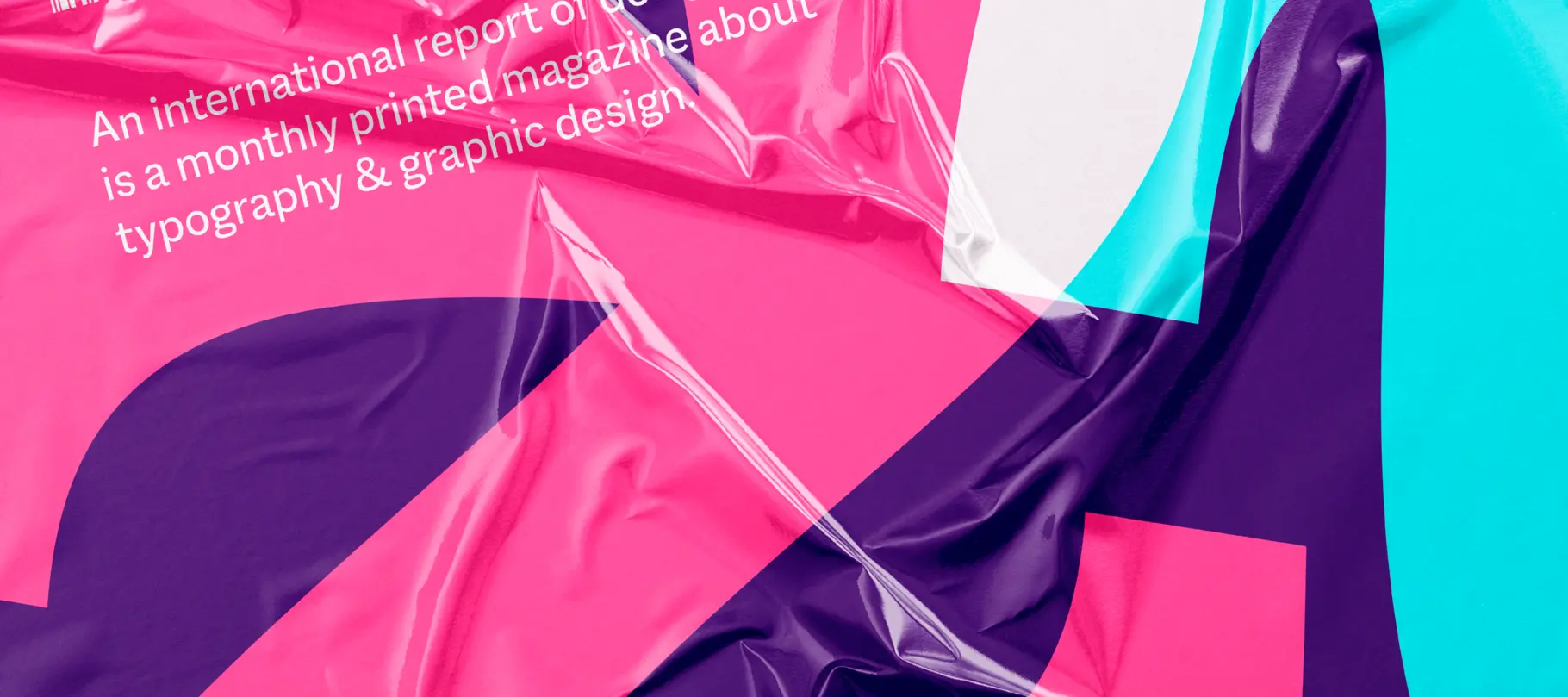
Macklin™
Inspiriert von der Tradition. Entwickelt für modernes Design.
Macklin ist inspiriert von der Zeit, als die Schrift von den Seiten der Bücher auf Großplakate und Anzeigen drängte. Mit einer klaren Weiterentwicklung gegenüber ihren typografischen Vorbildern ist die Superfamilie Macklin mit ihren scharfen und doch eleganten Formen bestens geeignet für zeitgenössisches und modernes Design.
Die Superfamilie Macklin umfasst 4 Unterfamilien mit 9 Strichstärken von sehr fein bis sehr fett: Insgesamt 54 Schriften, die eine breite Palette an Möglichkeiten für den Gestalter eröffnen.
Die Arbeit am Konzept der Macklin begann mit der Erforschung historischer Unterlagen aus Europa und speziell Großbritannien zu Beginn des 19. Jahrhunderts, insbesondere der Arbeit des Schriftgestalters und Gießereibesitzers Vincent Figgins.
Es war eine Zeit großer sozialer Veränderungen – der Beginn der industriellen Revolution. Eine Zeit, in der Hersteller und Werbetreibende plötzlich begannen traditionelle Handschrift- oder Kalligraphie Schriften zu ersetzen und eine andere, mutige und aufmerksamkeitsstarke Typografie forderten. Typografen experimentierten mit innovativen neuen Schriftstilen, wie Fat Faces und Italiennes. Sie entwickelten viele Stile, die von Marken und Designern auch heute noch verwendet werden, wie z. B. stark serifenbetonte oder serifenlose Schriften.
Verlomme zollt Figgins‘ Arbeit mit der Macklin Respekt, überträgt das Designkonzept jedoch in die Neuzeit. Jede Unterfamilie wurde aus dem gleichen Skelett entworfen. Das gibt den Designern eine breite Palette an Möglichkeiten. Sie können kontrastreich gestalten, ohne sich über unharmonische Zusammenstellungen Gedanken machen zu müssen. Mit der Macklin erschafft Verlomme eine Superfamilie, die einen bruchlosen visuellen Ausdruck aus einem Guss ermöglicht.
Malou Verlomme ist Senior Type Designer bei Monotype und seit 2016 im Unternehmen. Seine Schrift Camille ist Teil der Sammlung des französischen Centre National des Arts Plastiques